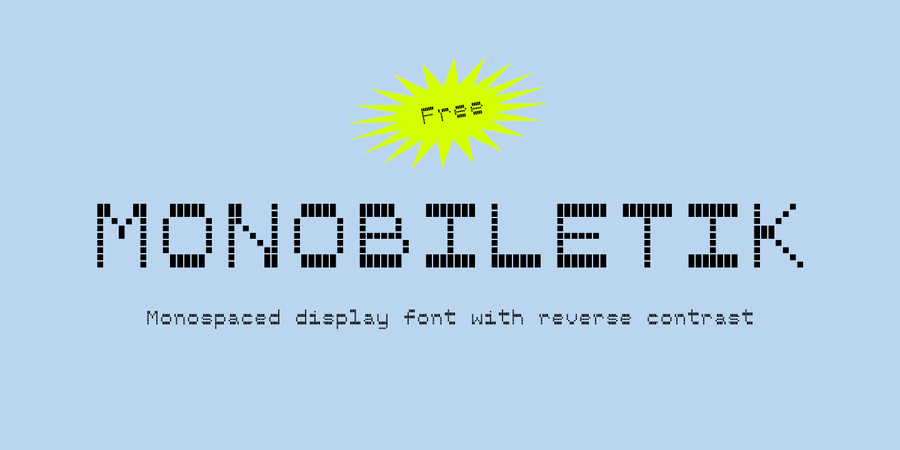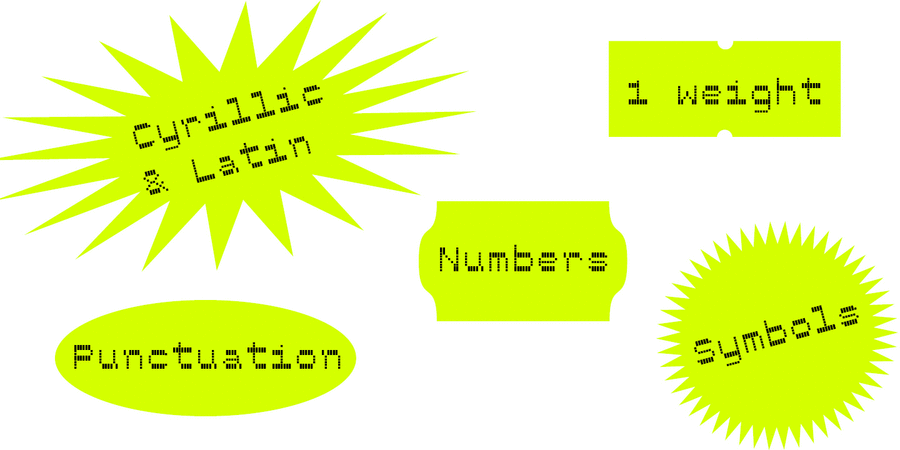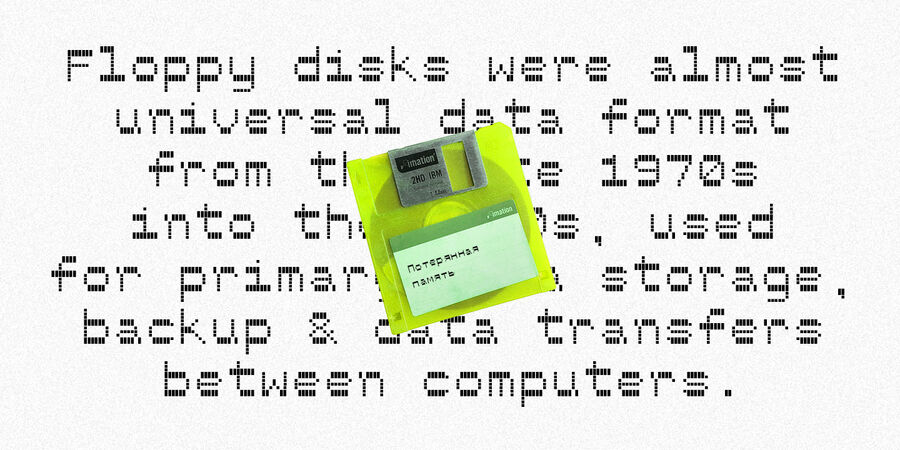
Опис шрифта MonobiletikМоноширинний піксельний шрифт зі зворотним контрастом. Monobiletik придатний для акцидентного використання, підтримує більшість європейських мов на основі кирилиці та латинки. Шрифт розробила Ольга Бутирська у 2020 році.
Особливості сімейства шрифтів MonobiletikХіт десятиліття:
Хіт 1970-х Хіт 1980-х Хіт 1990-х Monobiletik підтримує 83 мовиУкраїнська, Англійська, Німецька, Польська, Португальська, Іспанська, Французька, Російська, Чеська, Голландська, Італійська, Шведська, Турецька, Фінська, Білоруська, Сербська, Болгарська, Естонська, Литовська, Албанська, Африкаанс, Баскська, Бретонська, Валенсаска, Galician, Гельська (Шотландська), Данська, Індонезійська, Ірландська, Ісландська (Win), Каракалпацька, Каталонська, Норвезька, Окситанська, Ретороманська, Самі Лулі, Тсванська, Узбецька (Лат.), Фарерська, фризька, Чаморро, Естонська (Win), Південносаамська, Албанська (Win), Угорська, Верхньолужицька, Карельська, Латвійська (Mac), Литовська (Mac), Маорійські (Mac), Молдавська (Лат.), Нижньолужицька, Румунська (Win), Словацька, Словенська, Туркменська (Лат.), Хорватська (Win), Естонська (Mac), Курдська, Латишська, Маорійські, Руминська, Абазинська, Аварська, Агульська, Адигейська, Даргинську, Інгуську, Кабардино-Черкеська, Кабардинська, Карачаєво-Балкарська, Кумицька, Лакська, Лезгинська, Македонську, Мордовсько-Мокшанська, Мордовсько-Ерзянська, Ногайська, Рутульська, Табасаранська, Татська, Цахурська, Чеченська Функції сімейства шрифтів MonobiletikЗастосування гарнітури у верстці:
Асоціації з сімейством шрифтів MonobiletikОсобистість і характер гарнітури:
автоматичний, комп'ютерний, електронний, машинний, матричний, інженерний, прямий, байдужий, грайливий, дивний, оригінальний, прикольний, потішний
електроніка, автоматика, код, програмування, інженер, комп'ютер, робот, IT, айтішник, айті, технології, андроїд, залізо, хакер, комп'ютерна гра, математика, іграшка, ремонт, гаджет, девайс, гра, рентген, анімація Гарнітура асоціюється з віком: